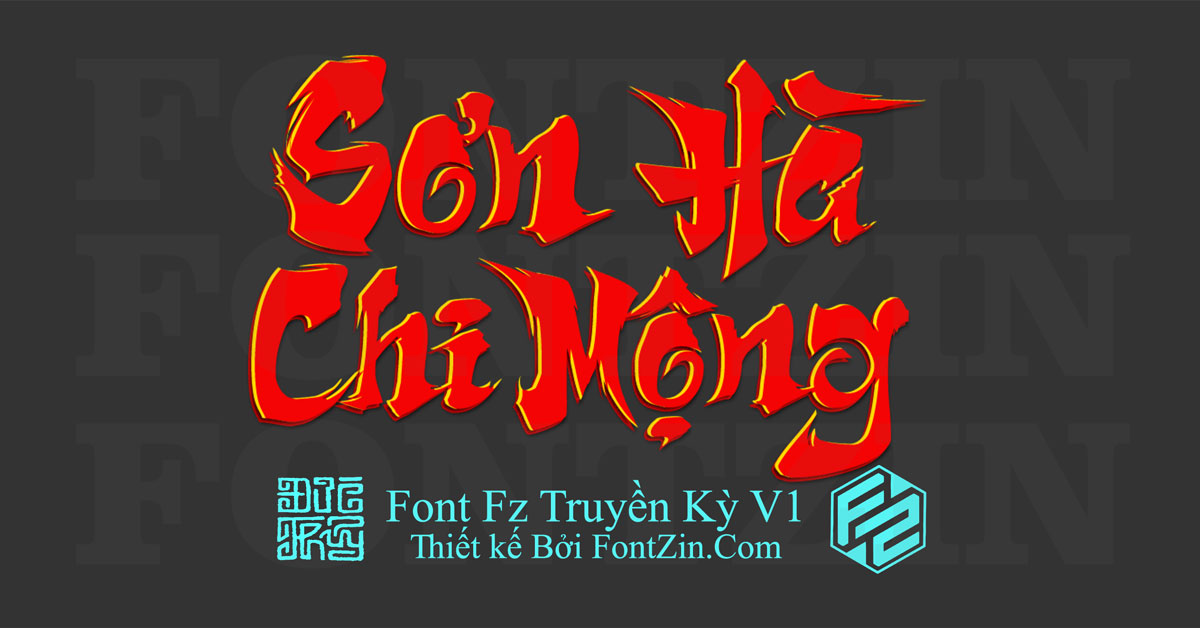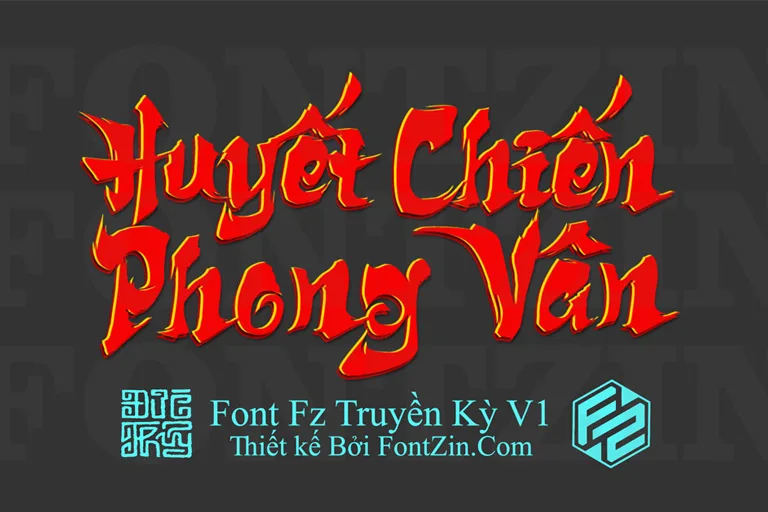
Font Game Kiếm Hiệp Fz Truyền Kỳ
Fz Truyền Kỳ – Bộ font chữ kiếm hiệp độc quyền, lấy cảm hứng từ những tựa game kinh điển: Võ Lâm Truyền Kỳ và Kiếm Thế.
Thiết kế bởi: FontZin
Thử sức và sáng tạo với Fz Truyền Kỳ trong thiết kế logo, biểu tượng, banner, poster gaming giúp bạn design 1 sản phẩm vè game dễ dàng hơn, độc đáo hơn và nhanh chóng.
Giới thiệu Font Game Truyền Kỳ
Bộ font chữ này được thiết kế bởi admin Đức Thủy, một trong những người tiên phong và có nhiều kinh nghiệm trong việc tạo ra những bộ font mang đậm phong cách game kiếm hiệp.
Đức Thủy cũng là một gamer kỳ cựu nên bộ font này cũng được anh ấy lấy cảm hứng hiết kế dựa trên các tựa game Truyền Kỳ mà anh ấy đang chơi.
Font làm game fz truyền kỳ tl
Font làm game Fz Truyền Kỳ TL
Bộ gaming font này tối ưu cho thiết kế Title game, nút bấm, UX, UI trong game.
1 Siêu phẩm Gaming Font
Font làm game Fz Truyền Kỳ phong cách độc đáo
Font game kiếm hiệp truyền kỳ
Bạt kiếm giang sơn - gaming font truyền kỳ
Bạt kiếm giang sơn – Gaming Font Truyền Kỳ
Sơn hà chi mộng - gaming font truyền kỳ
Sơn Hà Chi Mộng – Gaming Font Truyền Kỳ
Võ lâm trung nguyên - gaming font truyền kỳ
Võ lâm trung nguyên – Gaming Font Truyền Kỳ
Hồi ức kiếm thế truyền kỳ
Hồi ức Kiếm thế truyền kỳ
Huyết chiến phong vân
Huyết Chiến Phong Vân